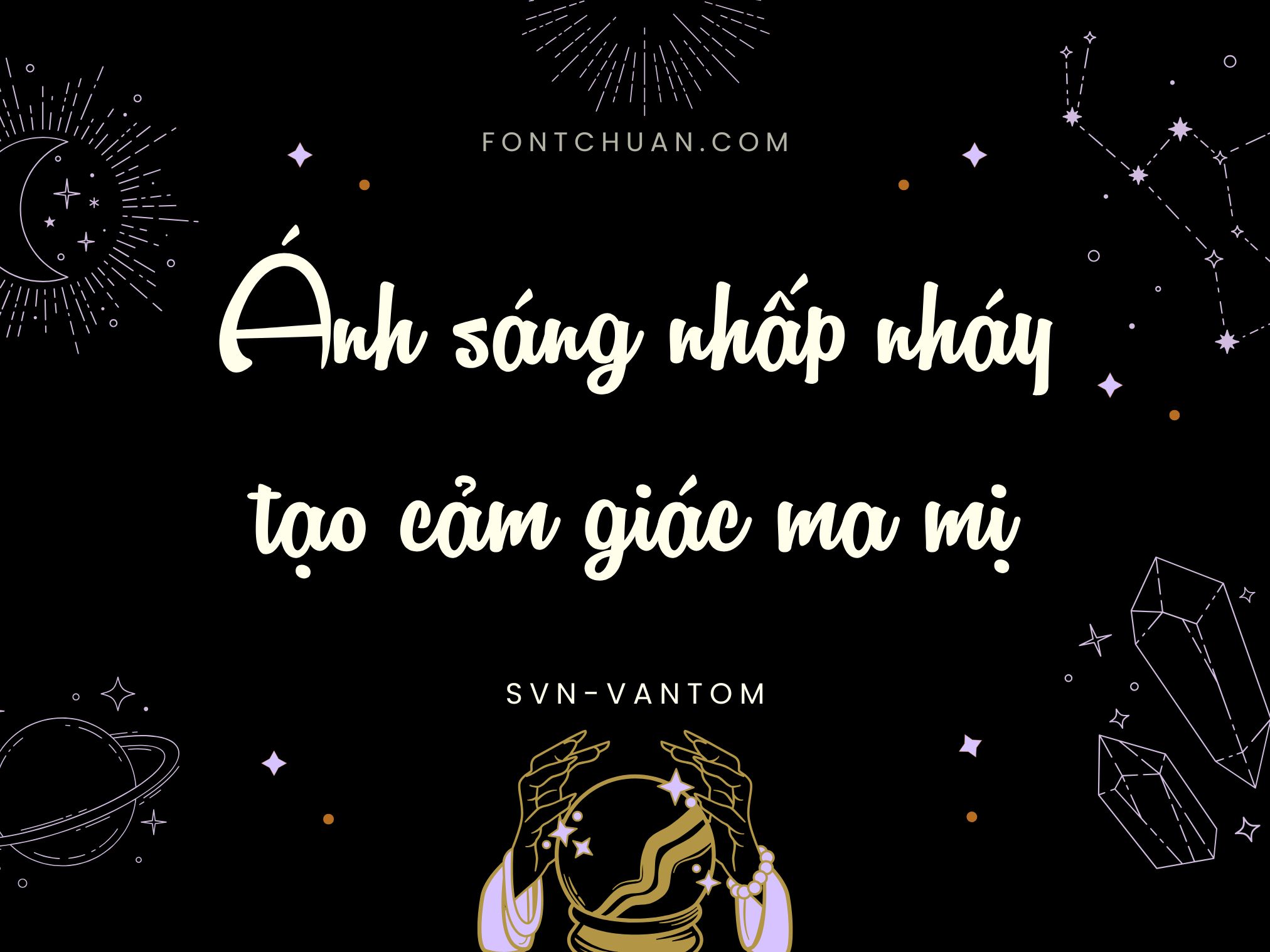
Font SVN Vantom Việt Hóa
Tác giả Font: Missinklab Studio
Font SVN Vantom là phiên bản Việt hóa của kiểu chữ Vantom, được thực hiện bởi Styleno.1 Fonts. Vantom là một Font Decorative viết tay với phong cách tự nhiên và thân thiện, bao gồm chữ hoa, chữ thường, chữ số và nhiều biến thể cho mỗi ký tự, cùng với các swash bổ sung. Font này hoàn hảo cho việc thiết kế logo, tiêu đề, thiệp mời, bao bì sản phẩm và các ấn phẩm quảng cáo khác.
SVN Vantom lý tưởng cho các dự án thiết kế yêu cầu sự cá nhân hóa và tinh tế, như thiệp mời, logo, tiêu đề và các ấn phẩm truyền thông. Các ngành nghề như thiệp cưới, ẩm thực và spa có thể tận dụng font này để tạo điểm nhấn trong thiết kế. Ngoài ra, font cũng thích hợp cho các sự kiện như Tết, Valentine, Sinh nhật và các lễ hội khác.